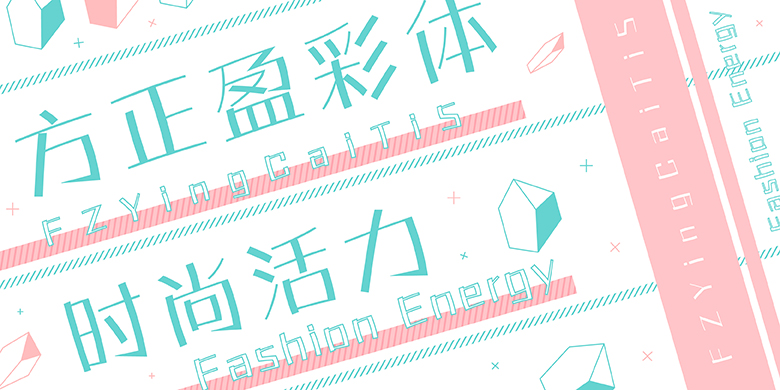
方正盈彩体系列
方正字库, , 设计师:郭炳权, 发行时间:2019, 字库编码:大陆简体(GB2312-80)、,简繁扩展(GBK), 分类:创意字体,
字体介绍:
盈彩体的创意灵感源于化妆品牌的宣传,于是借着它发挥为一款创意字体,由于宣传内容色彩缤纷,所以命名为“盈彩体”。盈彩体特点是横细直粗,横划,带小许抛离弧形,直划也是有小许弧度,全款字是没有一条垂直平行线的,摆脱传统。盈彩体充满动感和活力,多姿多彩,充分发挥女性魅力,它含8 款不同粗细字体!<br>适用于化妆类,时装类,体育类等商业宣传和包装设计。